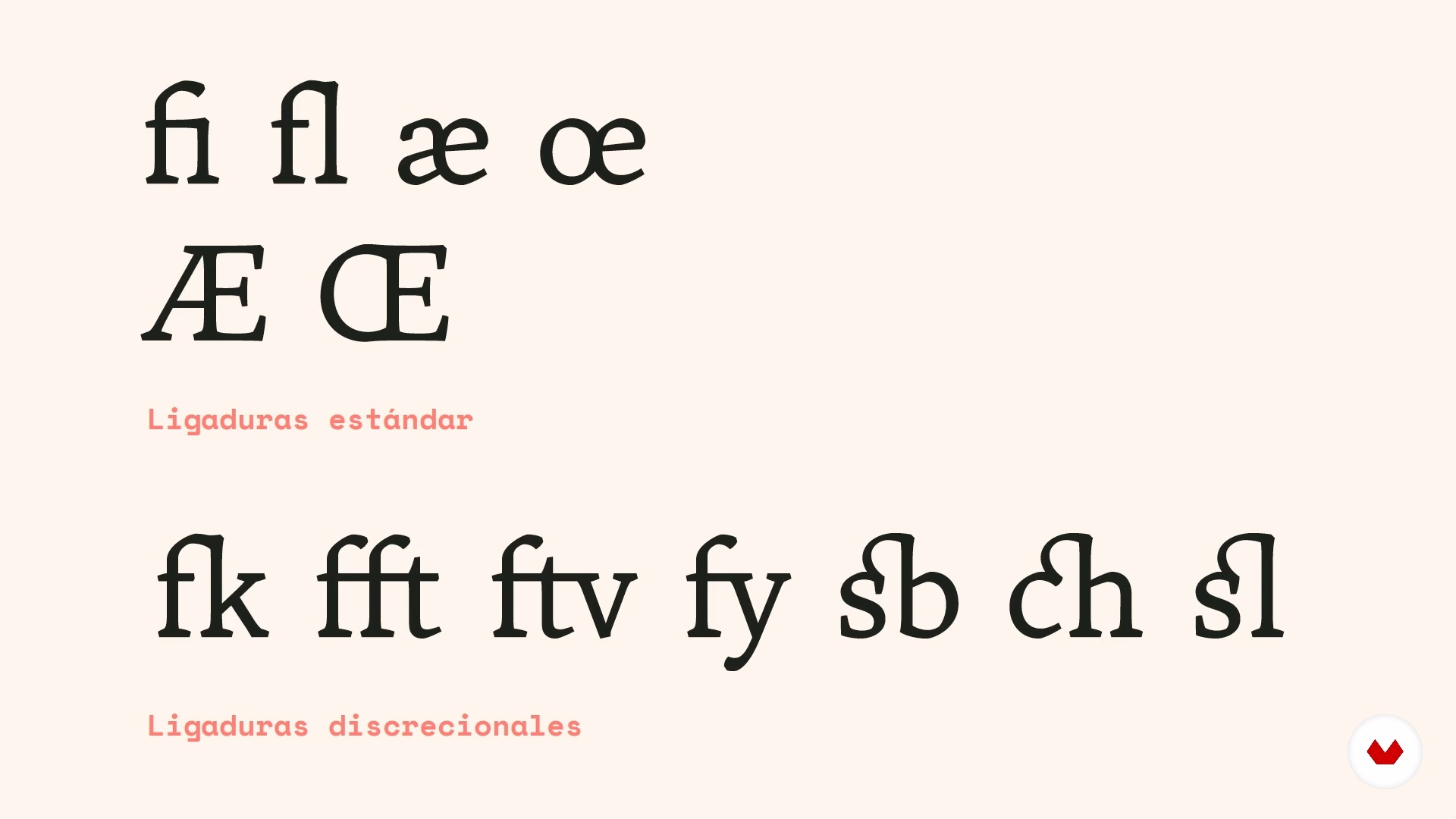
Digitale Neuinterpretation klassischer Schriftarten
Zeichensatz
Über die Videolektion: Zeichensatz
“Eine Schrift besteht nicht nur aus Groß- und Kleinschreibung. Es gibt eine Vielzahl von Glyphen, die wir so gestalten müssen, dass die Typografie voll funktionsfähig ist. ”
In dieser Videolektion behandelt Oscar Guerrero Cañizares das Thema: Zeichensatz, das Teil dieses Domestika-Onlinekurses ist: Digitale Neuinterpretation klassischer Schriftarten. Lernen Sie die Methode der typografischen Wiederbelebung kennen, um alten Schriftarten ein neues digitales Leben zu verleihen.
“Was denkst du? Zu diesem Zeitpunkt werden sie denken, dass wir kurz vor dem Abschluss stehen. Definieren Sie jedoch die High-Box und die Low-Box Es ist nur der Anfang des Prozesses. Schriftarten haben derzeit einen Zeichensatz die mindestens 256 Glyphen pro Schriftart haben wird, aber es hängt von den Eigenschaften des Projekts ab, Wenn es sich um eine Schriftart für Text handelt, wenn es ein Titel ist oder wenn es eine Familie ist, dass zusätzlich zu den 256 Zeichen enthalten, enthält andere Schriftarten, die Teil der Familiengruppe sind. Es ist wichtig, dass vor der weiteren Ergänzung des...”
Zusammenfassung des Kurses: Digitale Neuinterpretation klassischer Schriftarten